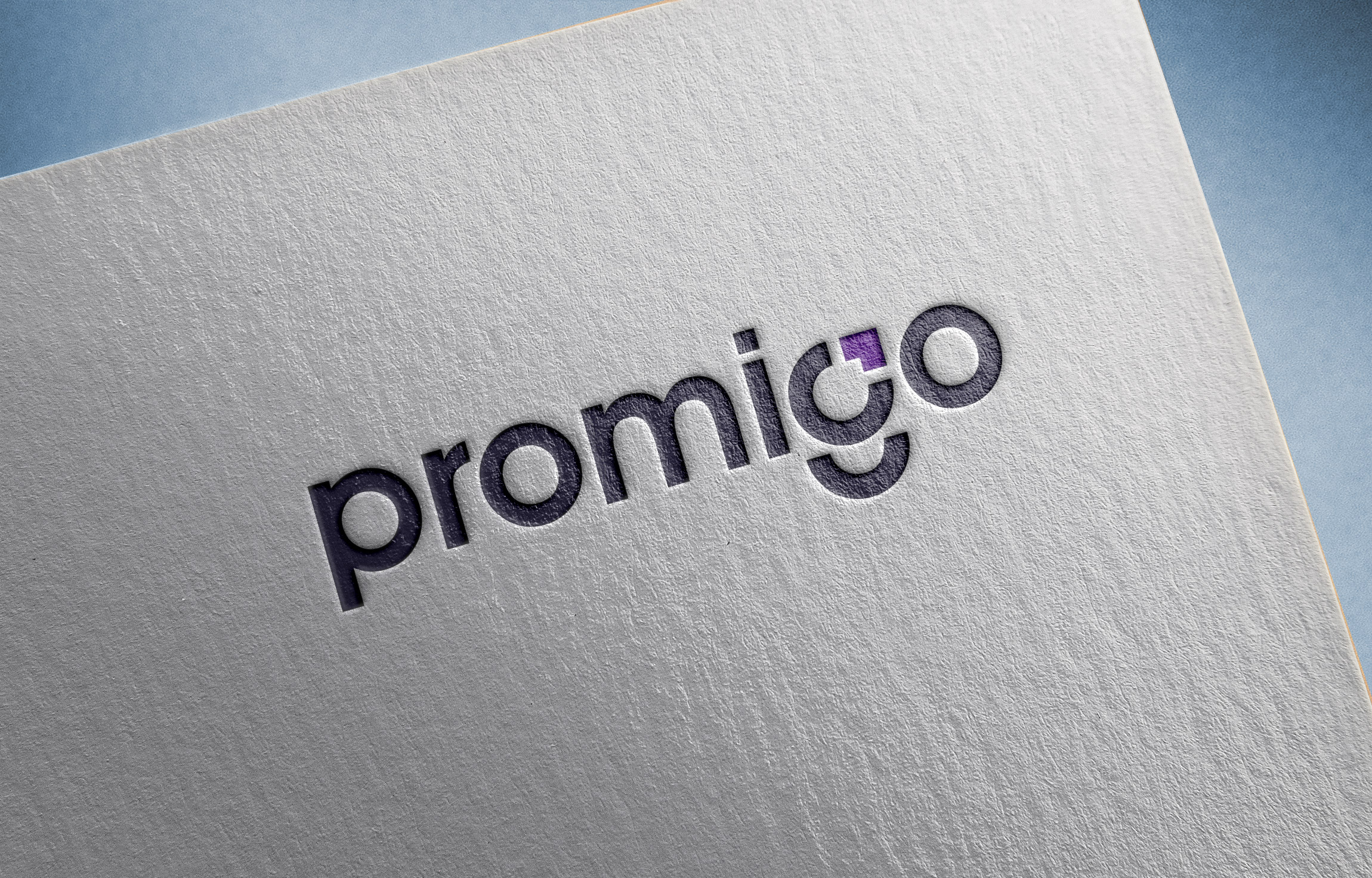
Markamıza Font Önerisi
Arkadaşlar selamlar yeni bir firma açıyorum logo olarak bir şeyler tasarladım çokta hoşuma gitti fakat font kısmında biraz kararsız kaldım.
Rounded yuvarlak tarzı bir font arıyorum tavsiye edeceğiniz bir font var mıdır?
https://fonts.google.com/specimen/Baloo+2#styles
Font ismi nedir hocam?
Quicksand - bold
https://www.dafont.com/poetsen-one.font?l[]=10&l[]=1
https://www.dafont.com/gogh.font?l[]=10&l[]=1
https://www.dafont.com/titan-one.font?l[]=10&l[]=1